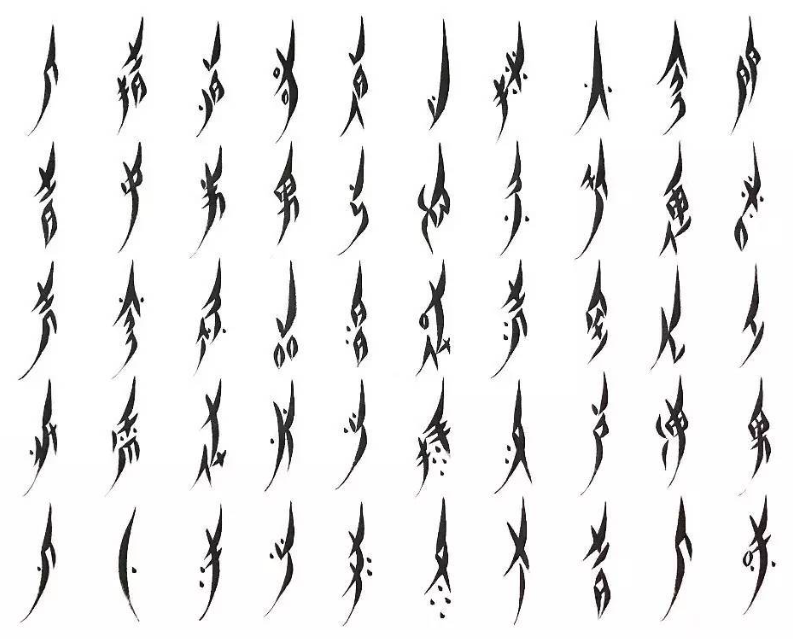
「女书」是世界上唯一一种专为女性存在的文字形式,专为女性而生,它起源于汉朝时期。在旧制度的统治下,许多女性受限于种种约束,无缘于识文断字的机会,因此无法倾诉个人的遗憾或生活的困苦。「女书」的诞生为这些女性开辟了一片表达的天地,成为了她们情感抒发的渠道。
1982年,这一文字被武汉大学宫哲兵教授在湖南省江永县所发现,因此又被称为“江永女书”。
女书的字形呈长菱形,字型秀丽娟细右上高左下低,呈现弯曲细小的形状,造型奇特。它常以绣品的形式出现,也被称为“绣字”。所有字符只有点、竖、斜、弧四种笔画,通篇没有标点符号,基本单字共有600个左右。